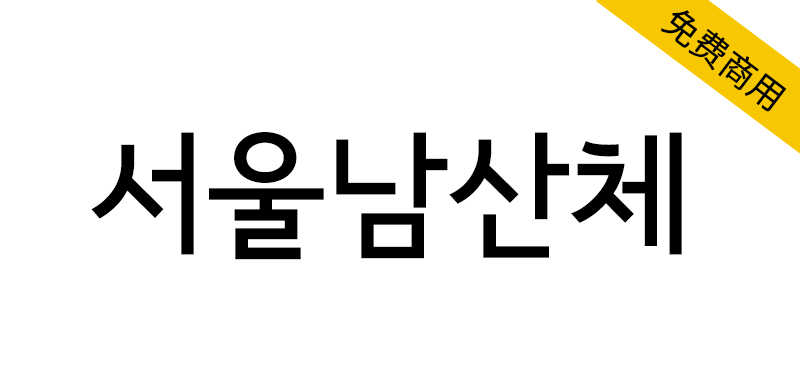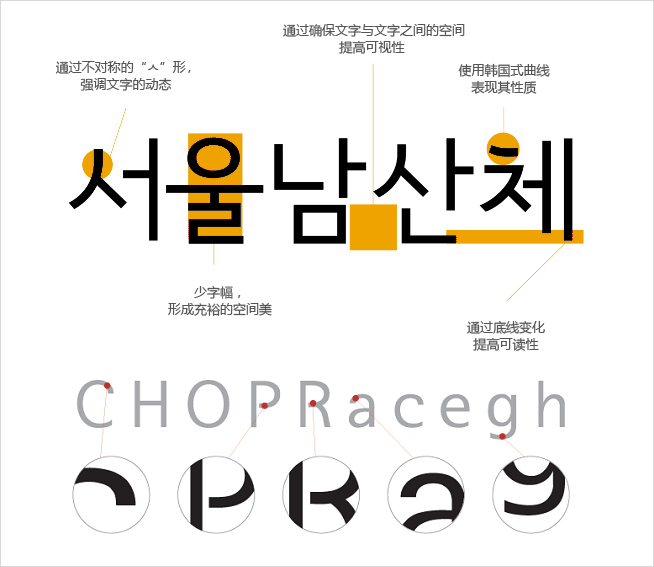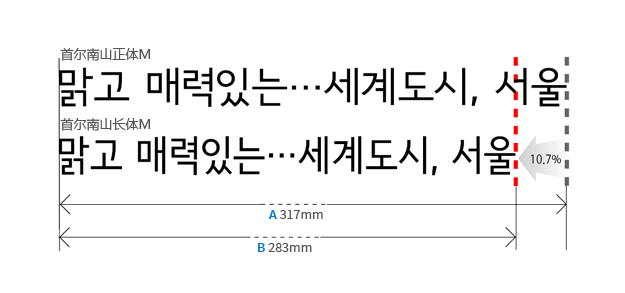
为提升城市认同性与品牌价值而开发出为普及首尔的固有字体,提升城市认同性与品牌价值,韩国首尔市开发出了哥特体系列的4种首尔南山体(Light、Medium、Bold、Extra Bold)。
首尔字体中蕴含着刚正的儒士精神和淡雅的留白之美,从造型上展现了韩屋的开放和瓦片的曲线美。此外,首尔字体取名时采用首尔两大代表性资源之一的“南山”,更能激发市民对韩民族固有美丽语言——韩文的文化自豪感。
首尔市将首尔字体作为首尔的固有字体而推广使用,首尔字体可提高城市认同性和品牌价值,开发了
首尔南山体4种(Light、Medium、Bold、Extra Bold)、竖写1种
首尔南山长体5种(Light、Medium、Bold、Extra Bold、black)。
首尔字体蕴含着正直的儒生精神和端庄典雅的含义,在造形上体现出韩屋的开放性和屋瓦的曲线美。
此外,字体名称运用了首尔代表性资源之一的“南山”,首尔字体将提高韩民族固美丽语言——韩文的文化自豪感。
通过不对称的“ㅅ”形,强调文字的动感
减少字幅,形成充裕的空间美
通过确保文字与文字之间的空间提高可视性
使用韩国式曲线表现其性质
通过底线变化提高可读性